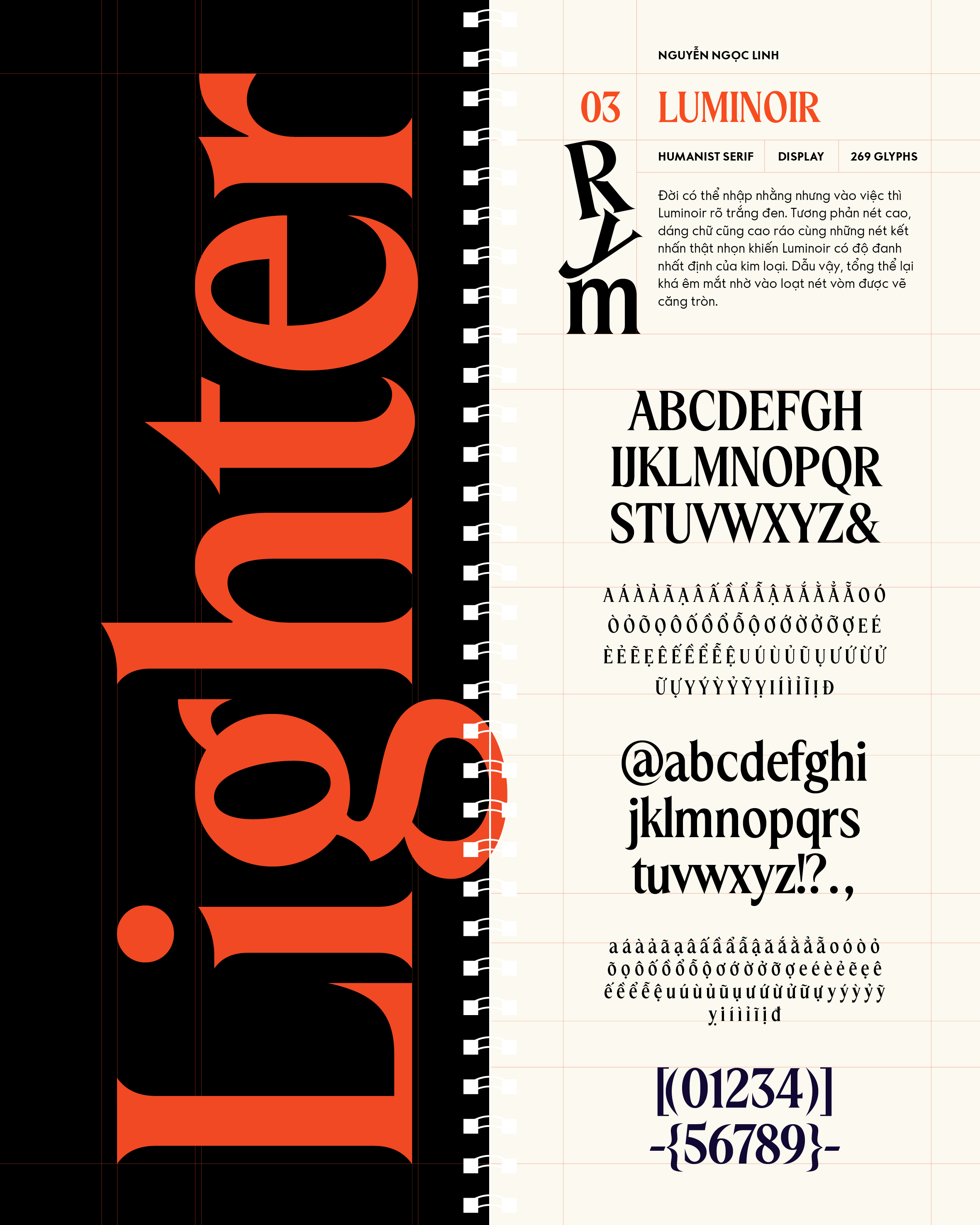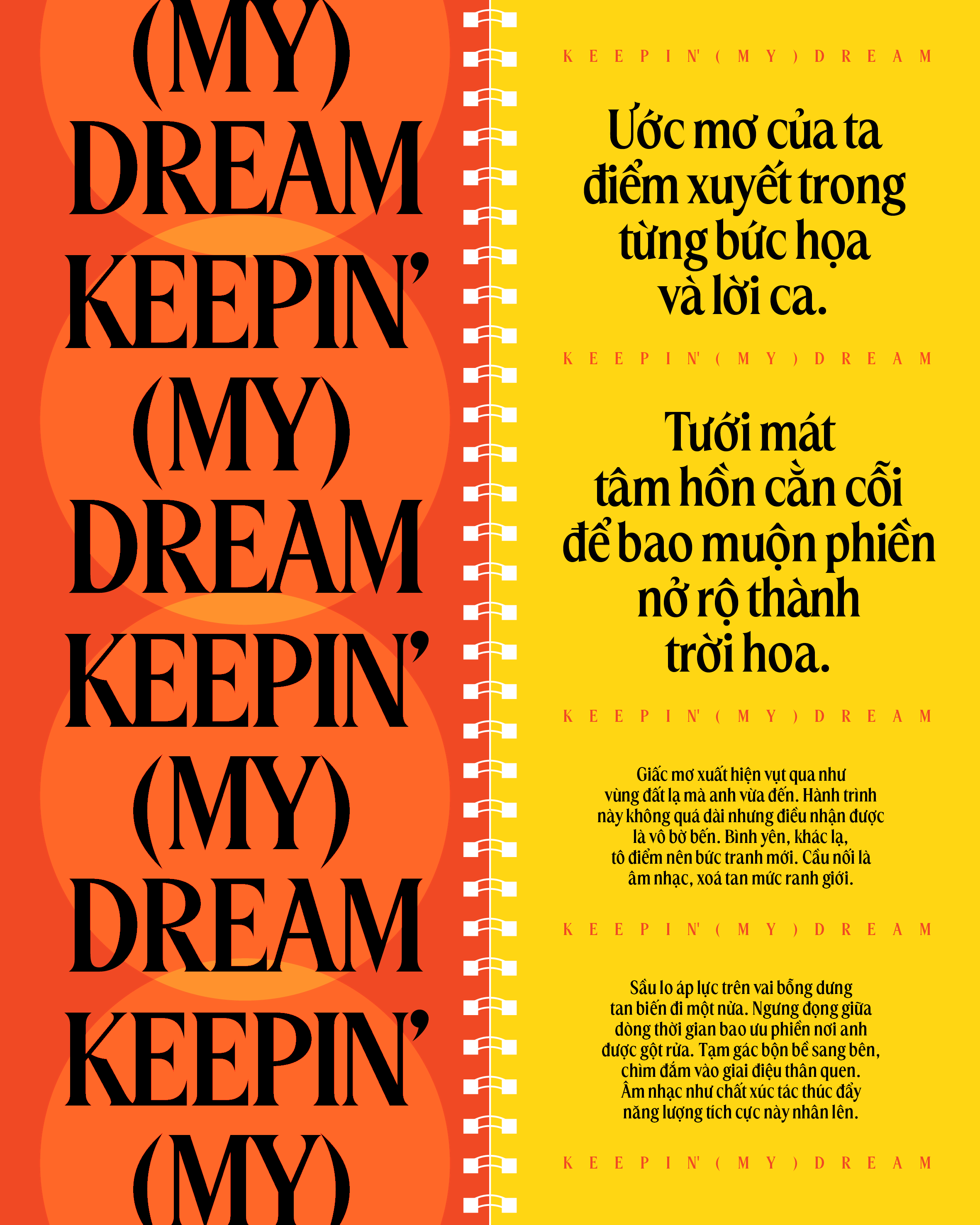
Luminoir
Về Luminoir: Đời có thể nhập nhằng nhưng vào việc thì Luminoir rõ trắng đen. Tương phản nét cao, dáng chữ cũng cao ráo cùng những nét kết nhấn thật nhọn khiến Luminoir có độ đanh nhất định của kim loại. Dẫu vậy, tổng thể lại khá êm mắt nhờ vào loạt nét vòm được vẽ căng tròn.
Humanist Serif
Display
Ngọc Linh